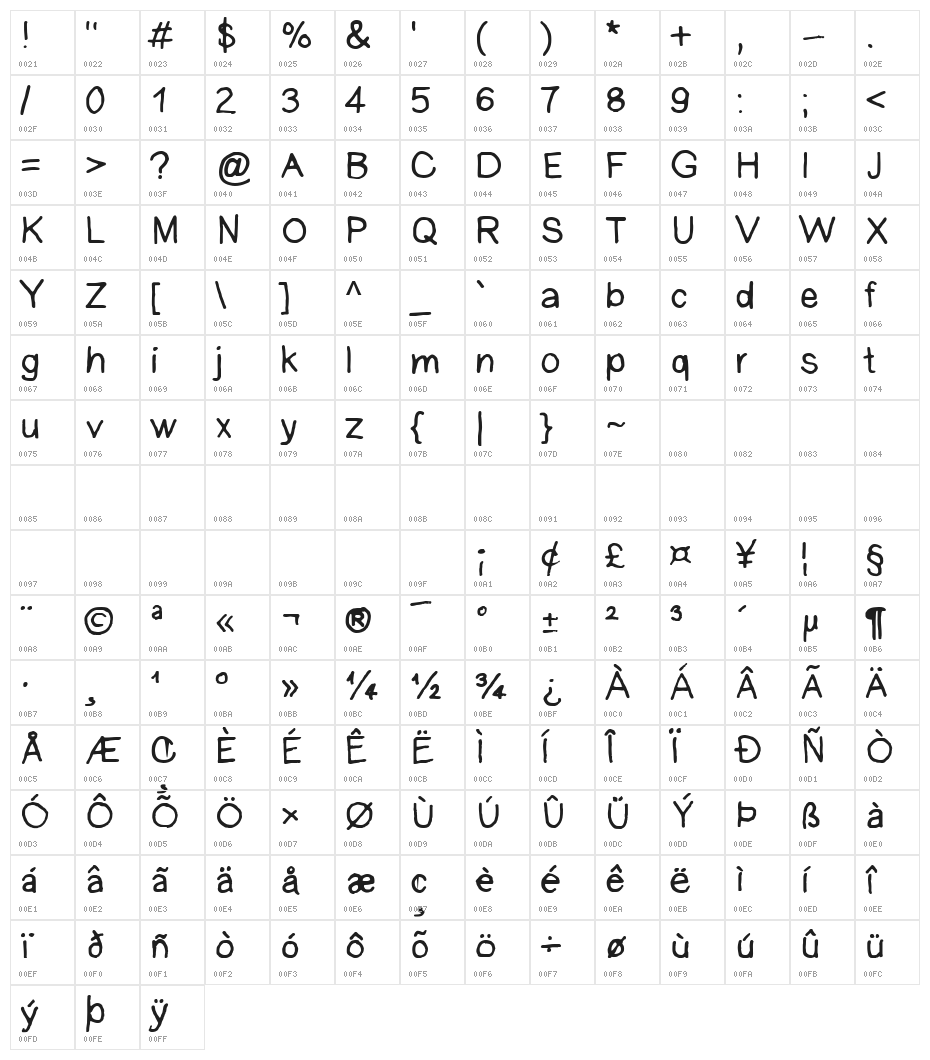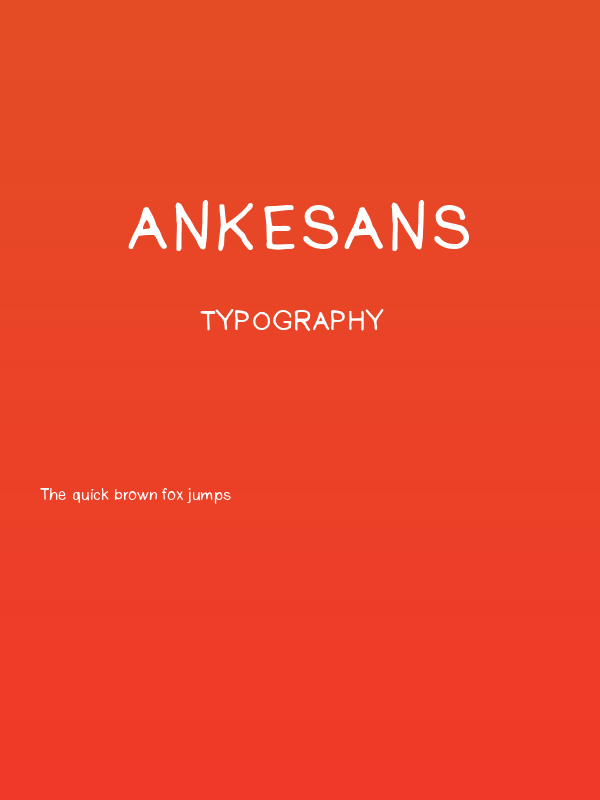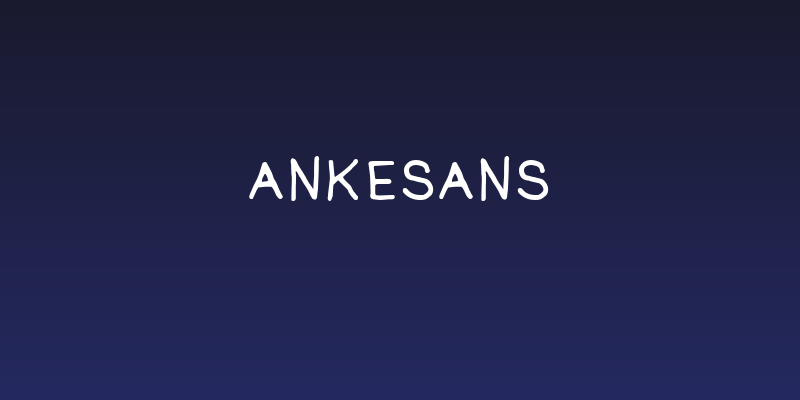
AnkeSans Font
| Stile generale | Casual |
| Caso d'uso | Headlines, Informal text, Creative projects |
| Progetti proposti | Ideal for children's books, greeting cards, casual branding, and playful social media graphics. |